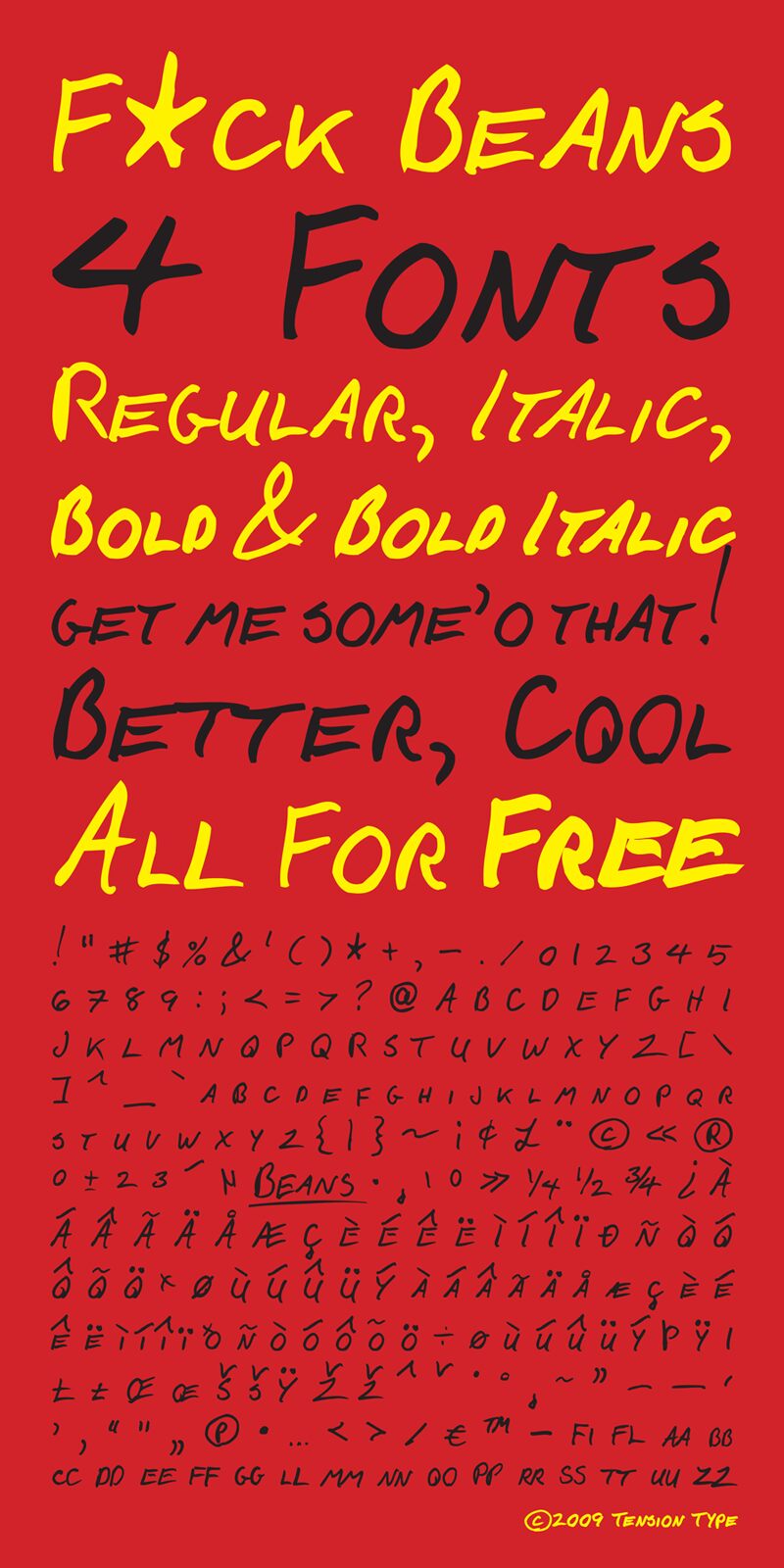
F*ck Beans Italic autorstwa Michael Tension to darmowy, odręczny krój pismowy typu display o szybkim, dynamicznym pociągnięciu liternictwa wykonanego markerem. Jego pochyłe pociągnięcia gwałtownie zmieniają szerokość, a kilka liter łączy się w niespokojną linię. Wykończenie jest surowe i bezpośrednie.
Ten zamaszysty, zakreślony ruch może nawiązywać do szkicowego rysunku postaci lub swobodnej ilustracji prasowej, dzięki czemu krój sprawdza się na plakatach muzycznych, grafikach odzieżowych (streetwear) i okładkach magazynów. Najbardziej przekonuje w niepokornym tytule lub haśle kampanii, gdzie ściśnięte połączenia i nagłe zakończenia pociągnięć mogą być odbierane jako część rysunku, a nie dopracowana typografia.